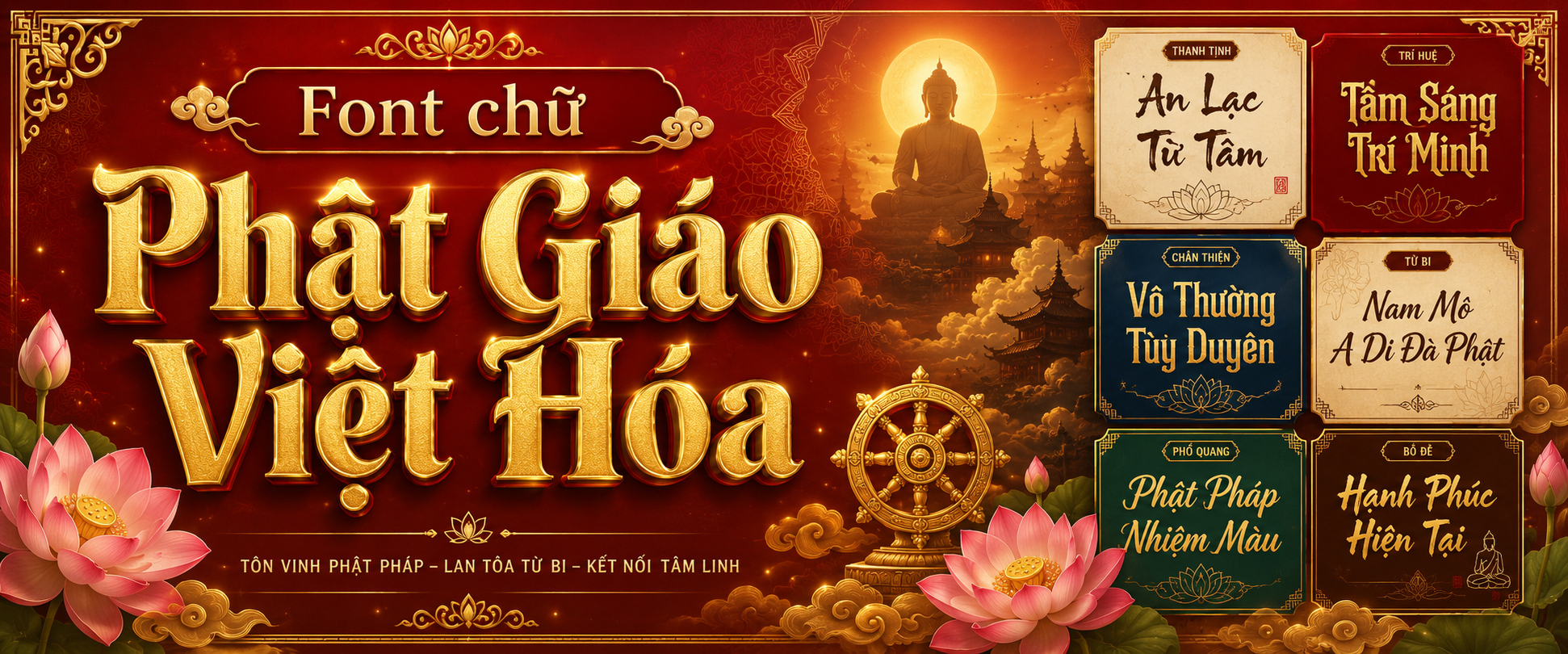
Trong thiết kế Phật giáo, font chữ không chỉ là phần hiển thị nội dung mà còn góp phần tạo nên thần thái của toàn bộ ấn phẩm. Một font phù hợp có thể làm poster trở nên trang nghiêm hơn, banner mềm mại hơn, và những câu chữ mang tinh thần thiền vị, thanh tịnh cũng dễ chạm cảm xúc người xem hơn. Trên s99.vn hiện không có một danh mục tách riêng hoàn toàn tên là “font Phật giáo”, nhưng lại có nhiều cụm rất gần với nhu cầu này như font thư pháp, font nhà chùa, font cổ trang, font Phật giáo và các font Việt hóa mang phong cách truyền thống. Dựa trên các nhóm kết quả đó, dưới đây là bài tổng hợp 10 font chữ Phật giáo đẹp trên s99.vn đáng tham khảo cho banner, poster, ảnh quote, backdrop lễ Phật đản và các ấn phẩm tâm linh.
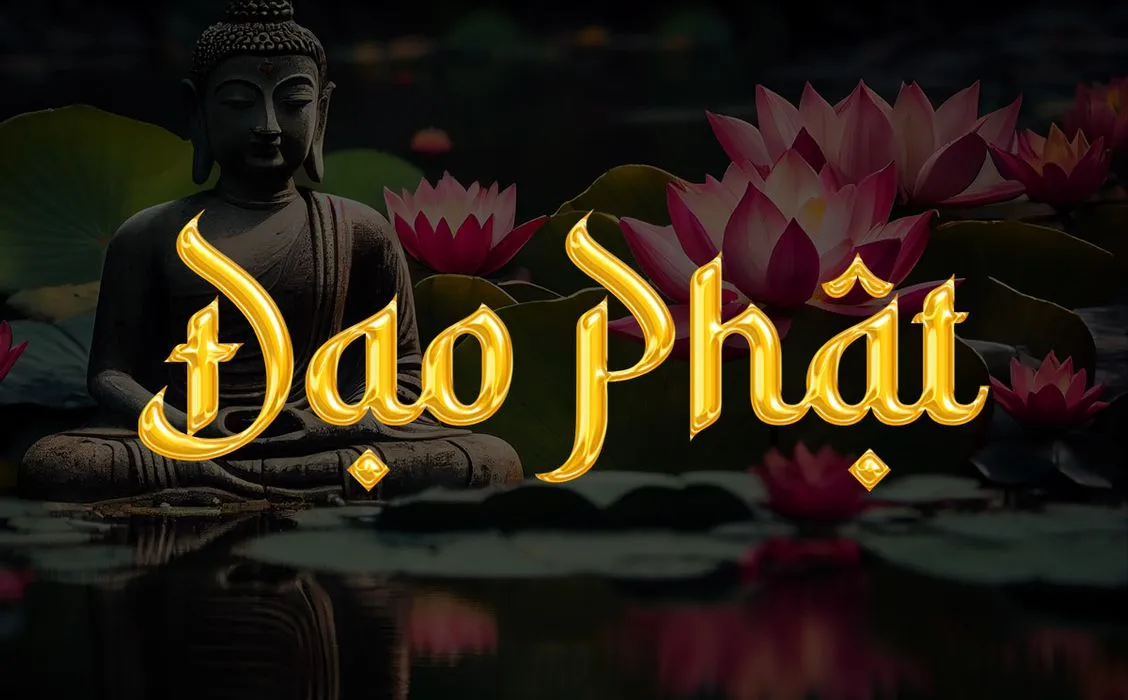
Đồ họa Phật giáo thường gắn với những yếu tố như sự trang nghiêm, thanh tịnh, mềm mại, truyền thống và chiều sâu văn hóa. Vì vậy, nếu dùng font quá hiện đại, quá công nghiệp hoặc quá vui nhộn, tổng thể thiết kế sẽ dễ bị lệch tinh thần. Ngược lại, những font mang hơi hướng thư pháp, cổ trang, nhà chùa hoặc có tiết tấu nét chữ mềm và uyển chuyển sẽ giúp ấn phẩm giữ được chất riêng. Trên s99.vn, ngay ở trang của font TH Hidayatullah Việt Hóa đã có các tag liên quan như font thư pháp, font cổ trang, font nhà chùa, còn bài blog về font UTM thư pháp cũng nhấn mạnh vai trò của font trong việc truyền tải tinh thần văn hóa và vẻ đẹp truyền thống trong các ấn phẩm lễ hội, tranh chữ và thiết kế mang hơi hướng dân tộc.
Nếu cần chọn một font tiêu biểu nhất cho đồ họa Phật giáo, UTM ThuPhap Thien An gần như luôn nằm trong nhóm đầu tiên nên thử. Theo bài blog của s99.vn về bộ 3 font thư pháp UTM, đây là một trong ba font thư pháp Việt hóa nổi bật và được giới thiệu cho những thiết kế cần yếu tố truyền thống, thẩm mỹ và bản sắc. Font này đặc biệt hợp với tiêu đề như Kính mừng Phật đản, Nam mô Bổn Sư Thích Ca Mâu Ni Phật, các câu thư pháp treo trang trí hoặc tiêu đề poster sự kiện Phật giáo. Nét chữ có độ bay vừa phải, không quá rối, nên phù hợp với cả ấn phẩm in lẫn thiết kế số.
Đây là font bạn yêu cầu thay vào danh sách, và thực tế nó cũng rất hợp với chủ đề Phật giáo. Trên s99.vn, TH Hidayatullah Việt Hóa được gắn các tag như font thư pháp, font cổ trang, font nhà chùa, arabic, việt hóa, cho thấy đây là một lựa chọn rất gần với nhóm thiết kế chùa chiền, tôn giáo và các bố cục mang hơi hướng phương Đông. Phần mô tả trên trang font cho biết Hidayatullah lấy cảm hứng từ nghệ thuật thư pháp, mang khuynh hướng truyền thống nhưng vẫn có nét hiện đại; font được thiết kế bởi Anthonie Van Hayu, được admin S99.VN Việt hóa, và hiện có loại file TTF. Với các thiết kế cần cảm giác cổ kính, nghiêm mà vẫn mềm, như bảng hiệu chùa, poster khóa tu, tiêu đề pháp hội hoặc ảnh quote Phật giáo, đây là một font rất đáng dùng.
Trong bài viết tổng hợp font thư pháp Việt hóa UTM trên s99.vn, UTM Azuki được xếp cùng nhóm với UTM ThuPhap Thien An và UTM Spring. So với Thien An, Azuki cho cảm giác nhẹ hơn, mềm hơn và dễ ứng dụng ở những bố cục cần độ thanh hơn là độ uy nghi lớn. Font này hợp để làm chữ phụ trong poster Phật giáo, câu kệ ngắn, tên chương trình, hoặc các ấn phẩm cần sự mềm mại như thiệp mời, hình quote, ảnh nền hoa sen hay thiết kế lời Phật dạy. Điểm mạnh của Azuki là giữ được hơi hướng thư pháp mà vẫn khá dễ đọc khi dùng ở cỡ chữ vừa.
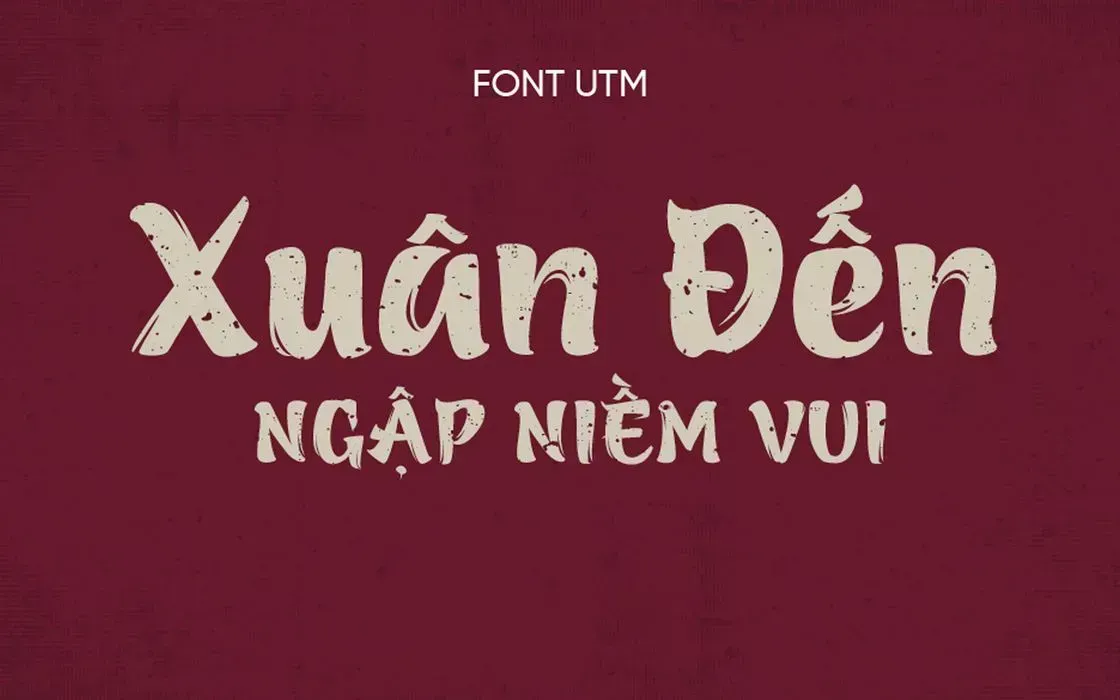
Trong trang của TH Hidayatullah Việt Hóa, phần “Cùng tác giả” hiển thị trực tiếp một mục tên Font Chữ Thư Pháp Fz Đức Thủy Tiếng Việt, cho thấy đây là một font được đặt cạnh những lựa chọn thư pháp và nhà chùa trên s99.vn. Nếu bạn cần một chất chữ thiên hẳn về thư pháp truyền thống, giàu cảm giác bút lông và khí chất Á Đông, thì Fz Đức Thủy là lựa chọn rất đáng thử. Font này hợp cho tiêu đề lớn, câu chữ treo chính giữa, hoặc những bố cục cần tạo cảm giác “đạo vị” rõ hơn là tính hiện đại. Trong thiết kế Phật giáo, đây là kiểu font mạnh về thần thái và thích hợp cho những dòng chữ mang tính trọng tâm.
Dù không mở riêng trang chi tiết trong lượt tra cứu này, cụm tìm kiếm font chữ thư pháp trên s99.vn đang là một nhóm kết quả rất lớn với hơn 1000 thiết kế, và trong danh sách font thư pháp liên quan có các tên gọi theo hướng đại tự, tiểu tự, bút bi và nhiều phong cách thư pháp khác nhau. Về mặt ứng dụng, những font mang tính đại tự thường đặc biệt phù hợp cho phần tiêu đề lớn trong poster Phật giáo, backdrop lễ Phật đản, tiêu đề ban thờ, hoặc các ấn phẩm cần một dòng chữ trung tâm đầy khí chất. Nếu mục tiêu của bạn là gây ấn tượng ngay ở phần đầu bố cục, nhóm font kiểu Đại Tự luôn là lựa chọn nên ưu tiên.
Cũng ngay trong trang TH Hidayatullah Việt Hóa, phần “Cùng tác giả” có hiển thị Font chữ thư pháp FZ Tiểu Tự Việt Hoá. Về mặt sử dụng, đây là kiểu font hợp cho những phần chữ nhỏ hơn, phụ đề, câu dẫn, câu thơ, đoạn trích ngắn hoặc lời chúc trong thiết kế Phật giáo. Khác với font tiêu đề lớn, font tiểu tự thường cần giữ được sự mềm mại nhưng không quá nặng nét, để khi đặt dưới ảnh tượng Phật, hoa sen hay nền vàng vẫn không làm bố cục bị bí. Với các ấn phẩm như quote Phật pháp, bìa tài liệu, thiệp lễ chùa, nhóm font tiểu tự thường rất hữu ích.
Trong kết quả tìm kiếm trên s99.vn với cụm gần phật giáo font việt hóa, nhóm font gợi ý không chỉ có thư pháp mà còn có các font mang cảm giác chùa chiền và Đông Nam Á. SVN-Nakhon Kanlaya là một trong những cái tên thường được người làm thiết kế nhắc đến khi cần không khí gần với chùa, nhà chùa, Phật giáo hoặc những bố cục mang tinh thần nghi lễ. Dù mình không trích được trang chi tiết riêng trong lần mở này, kết quả tìm kiếm của s99.vn cho thấy nhóm font dùng cho nhu cầu “phật giáo font việt hóa” là một cụm mạnh, và Nakhon Kanlaya là lựa chọn rất hợp nếu bạn cần cảm giác vừa nghiêm vừa có chất “đền chùa” rõ. Font này hợp cho bảng hiệu, tiêu đề chương trình, backdrop Phật giáo và các dòng chữ trang trí chủ đạo.
Trong cụm tìm kiếm font Việt hóa liên quan tới phong cách Phật giáo, cổ trang và nhà chùa trên s99.vn, các font theo hướng cổ điển, vintage, cổ trang thường rất phù hợp để phối với đồ họa Phật giáo, nhất là những ấn phẩm muốn tạo cảm giác trầm, xưa và có chiều sâu lịch sử. TH Seraphytes là một lựa chọn như vậy. Font này không phải thư pháp thuần, nhưng lại có khí chất cổ điển, hợp cho tên chương trình, tiêu đề phụ hoặc các phần chữ cần độ rõ hơn thư pháp nhưng vẫn không mất vẻ trang trọng. Đây là kiểu font nên dùng khi bạn muốn poster Phật giáo nhìn chững chạc, cổ kính và sang hơn.
Nếu phải chọn ra 3 font nổi bật nhất cho đồ họa Phật giáo trên s99.vn ở thời điểm này, mình sẽ ưu tiên UTM ThuPhap Thien An, TH Hidayatullah Việt Hóa, và Fz Đức Thủy Tiếng Việt. Ba lựa chọn này đại diện khá rõ cho ba sắc thái quan trọng của thiết kế Phật giáo: trang nghiêm, cổ trang – nhà chùa, và thư pháp truyền thống. Bên cạnh đó, các font như UTM Azuki, Tiểu Tự, SVN-Nakhon Kanlaya, TH Seraphytes hay TH Kagestone sẽ giúp bạn mở rộng thêm nhiều hướng phối chữ khác nhau tùy từng ấn phẩm.